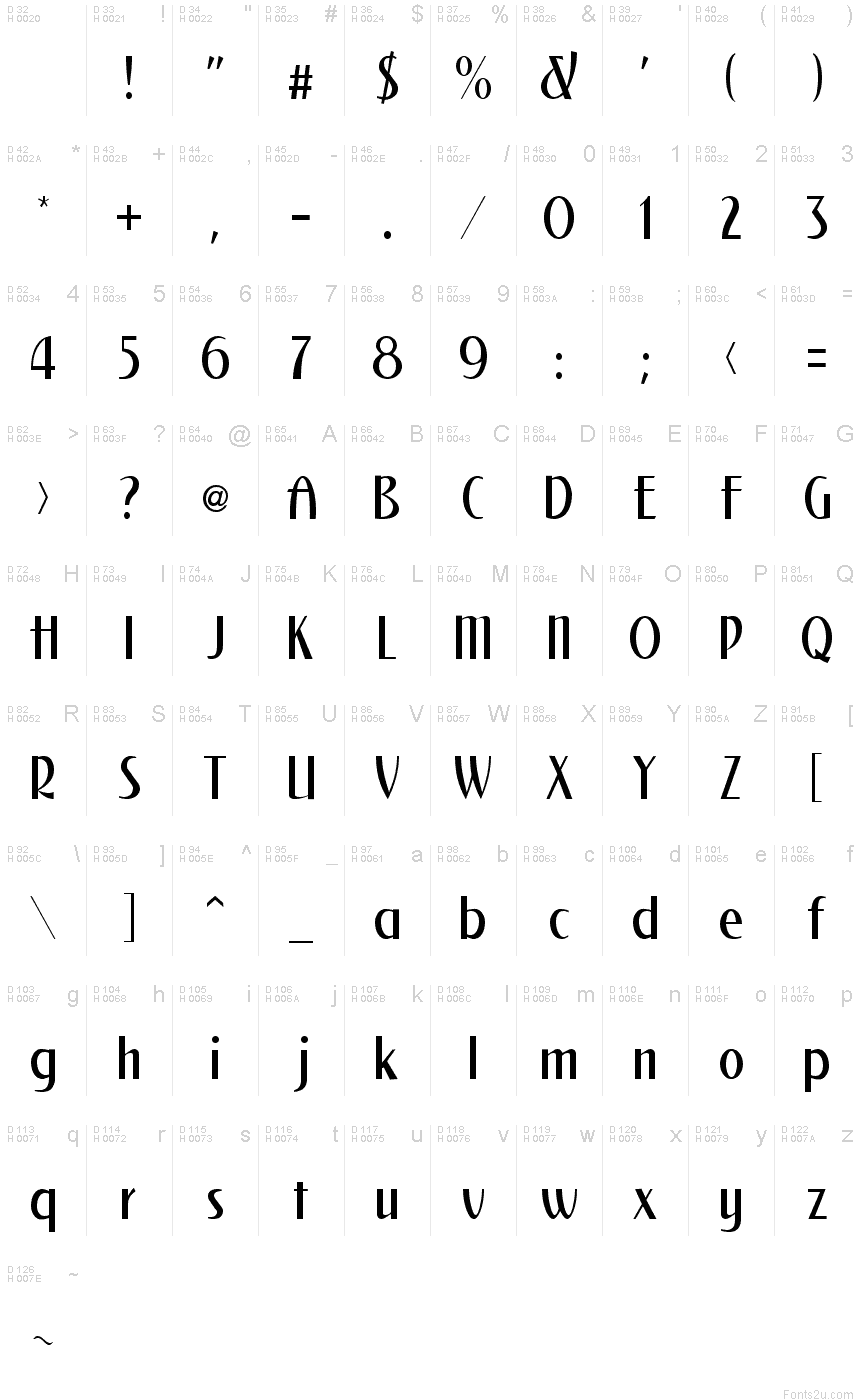
New Forum Light od Thomas E. Harvey to darmowy, kontrastowy krój szeryfowy typu display o niekonwencjonalnym profilu. Szerokie pionowe kreski łączą się z cieniutkimi, włoskowatymi łukami, a zaokrąglone litery przechodzą w głębokie, spiczaste łączenia o zdecydowanie eksperymentalnym charakterze.
Jej płynne krzywe mogą nawiązywać do fotografii modowej i kanciastych ilustracji na okładkach magazynów lub plakatach kulturalnych. Sprawdza się również w identyfikacji wizualnej butików oraz projektowaniu okładek płyt. W projektowaniu edytorskim liternictwo potrafi zmienić nagłówek okładkowy w część obrazu, a nie tylko w neutralny podpis.